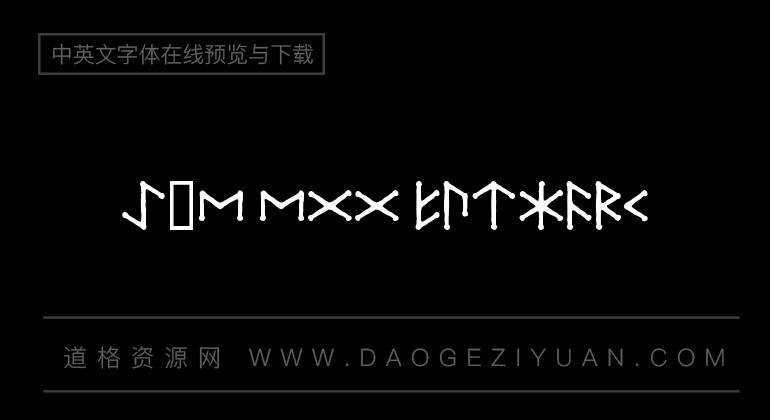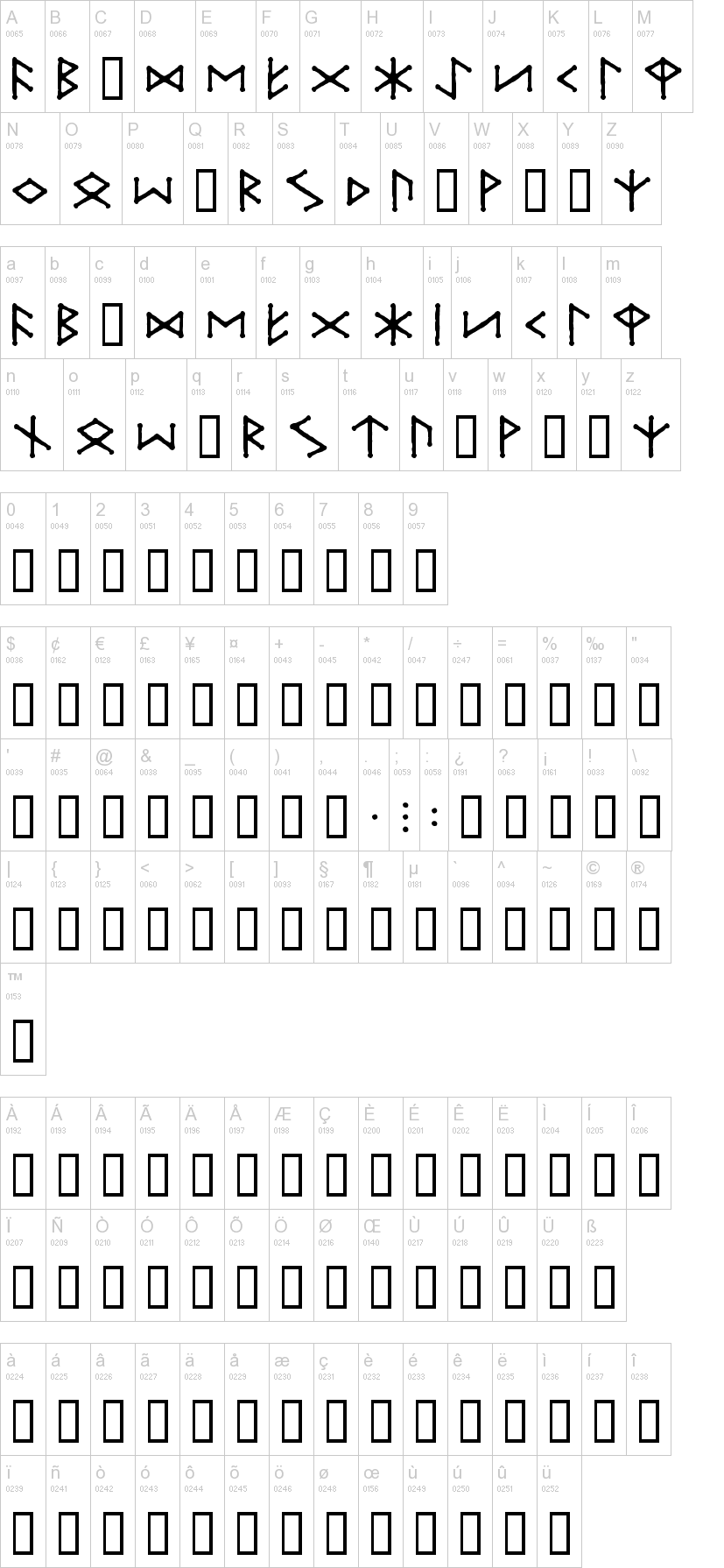
Ice Egg Futhark 是一种基于北欧符文的字体,其字母形状和构造都与传统的符文有所不同。它是由瑞典设计师 Johan Waldenström 创造的,被描述为一个现代化的符文字体。 Ice Egg Futhark 将传统符文的古老感与现代设计的干净线条相结合,创造出了一种独特的字体风格。它的字母形状结构简单且易于辨认,同时也有一些现代字体的特点,如线条的粗细变化和角度弯曲。 Ice Egg Futhark 字体适用于多种设计用途,如海报设计、标志设计、印刷设计等。因为其独特性和易于辨认性,这种字体也非常适合在品牌设计和标识中使用。内容介绍
Ice Egg Futhark是一款非常不错的手写艺术字体,具有很好的视觉感,适合于文化类的宣传设计、商业类品牌的广告和产品包装设计以及个性化文字排版等较多场景。